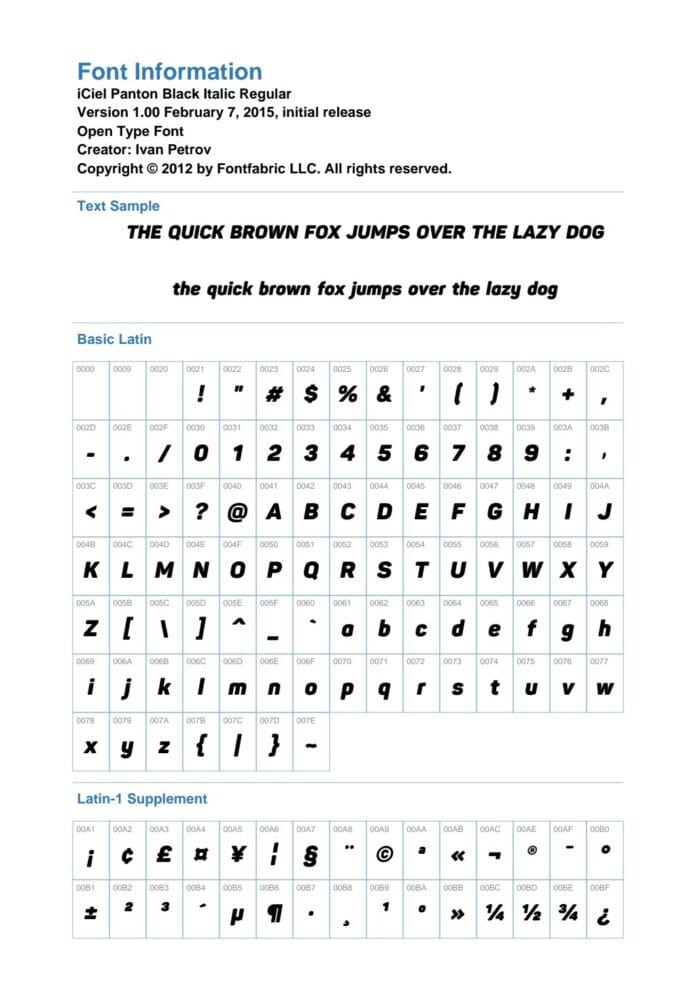
Font iCiel Panton Black Italic OTF Mạnh Mẽ: Tải ngay font chữ iCiel Panton Black Italic định dạng OTF, mang phong cách mạnh mẽ, hiện đại và chuyên nghiệp. Hoàn hảo cho các tiêu đề, logo, và ấn phẩm thiết kế đòi hỏi sự nổi bật và cá tính.
Giới thiệu về Font iCiel Panton Black Italic
Được phát triển dựa trên bộ font Panton nổi tiếng của Fontfabric LLC và được Việt hóa bởi iCiel, phiên bản Black Italic này thừa hưởng tất cả những ưu điểm vượt trội về tính thẩm mỹ và kỹ thuật. Nó mang đến sự linh hoạt đáng kinh ngạc cho các nhà thiết kế, từ những người chuyên nghiệp dày dặn kinh nghiệm đến những ai mới bắt đầu hành trình sáng tạo của mình. Dù bạn đang thực hiện một dự án branding, thiết kế poster, banner quảng cáo, hay chỉ đơn giản là cần một tiêu đề ấn tượng, iCiel Panton Black Italic chắc chắn sẽ không làm bạn thất vọng. Hãy cùng khám phá sâu hơn về những đặc điểm nổi bật và lý do tại sao phông chữ này lại là một phần không thể thiếu trong bộ sưu tập của bạn.
iCiel Panton Black Italic không chỉ đẹp mà còn có nhiều tính năng kỹ thuật và thẩm mỹ nổi bật, biến nó thành một công cụ đắc lực cho các nhà thiết kế:
Phong cách Thẩm mỹ Độc đáo
- Mạnh mẽ và Hiện đại: Với độ đậm đặc trưng của biến thể ‘Black’ kết hợp với nét nghiêng táo bạo, phông chữ này toát lên vẻ mạnh mẽ, năng động và hiện đại. Nó ngay lập tức thu hút sự chú ý và truyền tải thông điệp một cách rõ ràng, dứt khoát.
- Cá tính và Năng lượng: Nét nghiêng không chỉ tạo sự uyển chuyển mà còn thêm vào một chút kịch tính, sự chuyển động, khiến các tiêu đề trở nên sống động và đầy năng lượng. Điều này đặc biệt hữu ích cho các thương hiệu muốn thể hiện sự trẻ trung, đổi mới và tiến bộ.
- Độ đọc cao: Mặc dù đậm và nghiêng, iCiel Panton Black Italic vẫn giữ được độ dễ đọc đáng kinh ngạc nhờ vào tỷ lệ và khoảng cách ký tự được tối ưu hóa. Điều này làm cho nó trở thành lựa chọn tuyệt vời cho các tiêu đề, slogan, và các đoạn văn bản ngắn cần sự nổi bật.
- Tính chuyên nghiệp: Được thiết kế bởi Fontfabric LLC, một studio font uy tín, iCiel Panton Black Italic mang trong mình sự tinh tế và chuyên nghiệp, phù hợp cho cả các dự án thương mại cao cấp.
- Bộ ký tự đa dạng: Bao gồm đầy đủ các ký tự Latin cơ bản (chữ hoa, chữ thường, số, dấu câu) và bộ ký tự Latin-1 Supplement, hỗ trợ nhiều ngôn ngữ châu Âu và các ký hiệu đặc biệt. Điều này đảm bảo rằng bạn có thể sử dụng font này cho nhiều loại nội dung khác nhau mà không gặp hạn chế về ký tự.